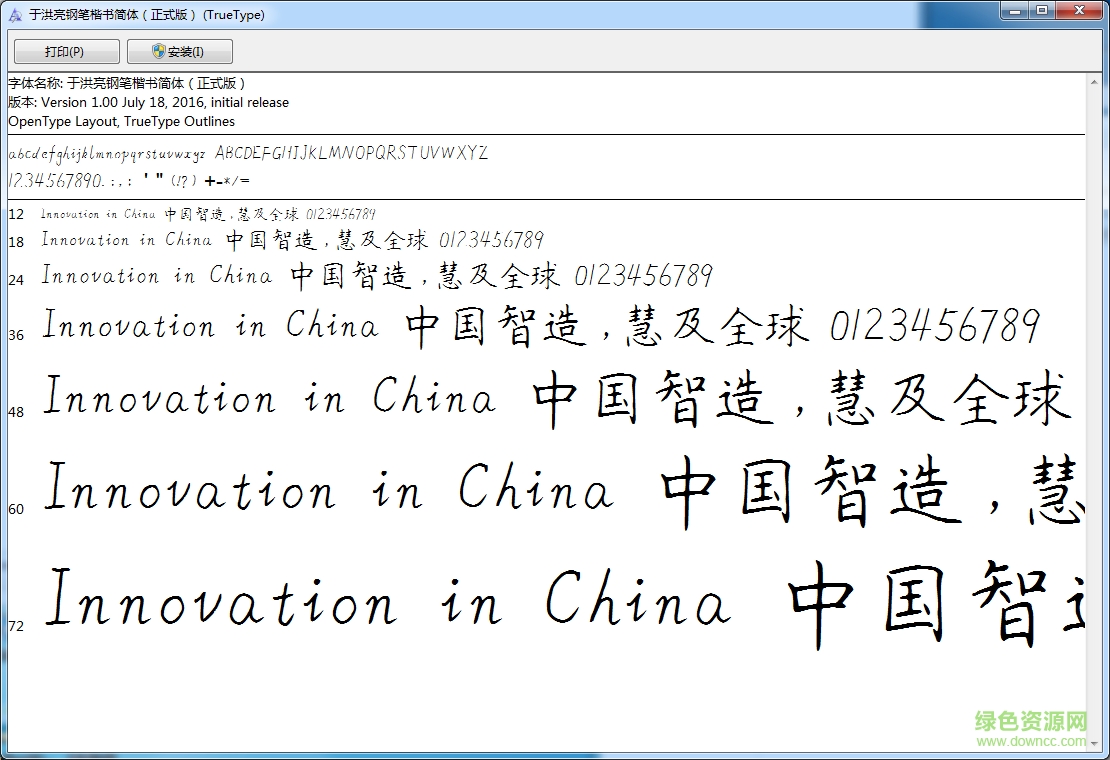
軟件介紹 軟件標(biāo)簽: 于洪亮鋼筆楷書簡體 于洪亮字體 字體 于洪亮鋼筆楷書簡體是一款簡單大方的鋼筆字體,字體端正簡單極具個性,使用簡單如行云流水一般。快來綠色資源網(wǎng)下載體驗吧!于洪亮鋼筆楷書簡體介紹于洪亮鋼筆楷書字體是一款非常不錯的字體,字形強(qiáng)韌有勁并且?guī)в兴囆g(shù)氣息,非常適合鋼筆楷書設(shè)計方面,喜歡的用戶可以在本站進(jìn)行下載使用。于洪亮鋼筆楷書字體安裝方法一:控制面板/字體/文件/安裝新字體;方法二:直接將字體復(fù)制到C:\WINDOWS\Fonts。方法三:針對win7系統(tǒng),用戶只需選中字體右鍵安裝即可。 軟件截圖 上一張下一張(1 / 1) 安裝詳細(xì)截圖 猜你喜歡 鋼筆字體 楷書字體 鋼筆字體 鋼筆字體是設(shè)計領(lǐng)域經(jīng)常用到的字體,鋼筆字體具有鮮明的個人特征,風(fēng)格多樣,深受廣告設(shè)計、平面設(shè)計師的喜愛,除了一些手寫鋼筆字體,還有正楷、行書類的鋼筆字字體,為設(shè)計師們提供了豐富的字體形式,綠色資源網(wǎng)也有很多鋼筆字體下載和鋼筆字體包,需要的可以看一看 查看更多>> 鋼筆書法軟件手機(jī)版 93.56M/中文/10.0/v2.1.5 安卓版下載 鋼筆之家 4.83M/中文/10.0/v1.0.2 安卓版下載 鋼筆手寫字體免費 11.71M/中文/1.2/下載 鋼筆書法入門基知識 31.79M/中文/5.0/v6.3.1 安卓版下載 浮生體 1.92M/中文/5.0/下載 伯樂鋼筆行書字體 3.53M/中文/6.6/下載 楷書字體 楷書字體是綠色資源網(wǎng)小編專為大家收集的一類非常流行而且好用的楷書字體,它包括了各種形式的楷書??瑫步姓?、真書、正書。從程邈創(chuàng)立的隸書逐漸演變而來,更趨簡化,橫平豎直,筆勢雄奇,姿態(tài)橫生,可應(yīng)用于繪畫設(shè)計、藝術(shù)創(chuàng)作、平面廣告、印刷包裝、電視廣告等等各行各業(yè)。也是現(xiàn)在很多行業(yè)必用的一類字體,小編收集的這一類楷書字體希望能更好的幫助大家收集和使用楷書字體。 查看更多>> 楷體國標(biāo)字體官方版 2.45M/中文/7.1/下載 漢儀閃耀楷書字體 1.77M/中文/0.0/下載 華為漢儀錦時楷書 2.92M/中文/5.0/下載 楷書字典手機(jī)版 4.46M/中文/5.0/v2.0 安卓版下載 經(jīng)典楷體繁體 3.96M/中文/5.0/下載 楷書繁體字體包 9.76M/中文/8.0/下載 其他版本下載 標(biāo)題 大小 更新日期 下載 下載地址 電腦版 于洪亮鋼筆楷書簡體 點擊報錯 軟件無法下載或下載后無法使用,請點擊報錯,謝謝! 關(guān)閉報錯反饋 請描述您所遇到的錯誤,我們將盡快予以修正,謝謝! *必填項,請輸入內(nèi)容 本類最新 dreamweaver字體庫 首爾南山體字體 v1.06 官方版 潮字社風(fēng)云簡ttf 潮字社凌渡鯤鵬簡體字體 潮字社曾玉波手書簡字體 微博慧心字體 相關(guān)文章 Photoshop字體安裝使用方法和技巧 如何解決“無法新增字體”問題 Win 7系統(tǒng)安裝字體方法 網(wǎng)頁字體大小設(shè)置方法 怎么改網(wǎng)頁字體大小 在Linux系統(tǒng)中安裝字體的幾種方法 windows7字體顯示問題:打開某些程序的時候顯示的是亂碼 用戶評論 熱門評論 最新評論 發(fā)表評論 查看所有評論(0) 昵稱: 請不要評論無意義或臟話,我們所有評論會有人工審核. 字?jǐn)?shù): 0/500 (您的評論需要經(jīng)過審核才能顯示)